TPフォント使用事例紹介 「webサイト その1」
パッケージや書籍、Webサイト、広告など各媒体でのタイププロジェクトのフォントの使われ方を事例を元にご紹介していきます。
今回は、Webサイトをまとめてご紹介します。
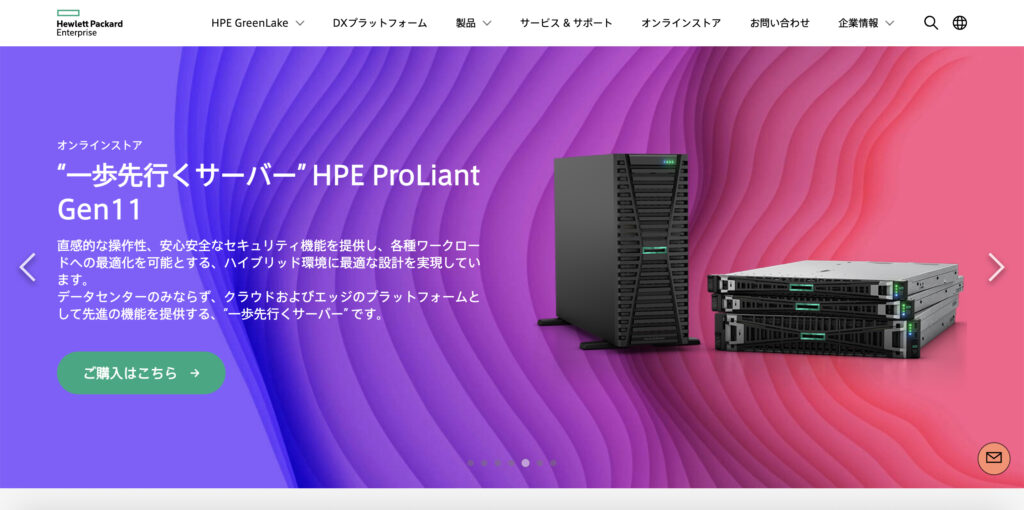
日本ヒューレット・パッカード合同会社
【使用されているタイププロジェクトのフォント】
AXIS Font ベーシック
主にAXIS Font ベーシック Rが全面的に使われています。フォントを統一しウエイト数も絞ったことでミニマルでスッキリとした、とても知的な印象を受けます。
明快かつ知的な表情の文字組みを得意とするAXIS Font ベーシックがとてもマッチしているように思います。また比較的、欧文の入るテキストが多いので、AXIS Fontの特徴の1つでもある和文と欧文を混植した際の相性の良さが効果を発揮しています。
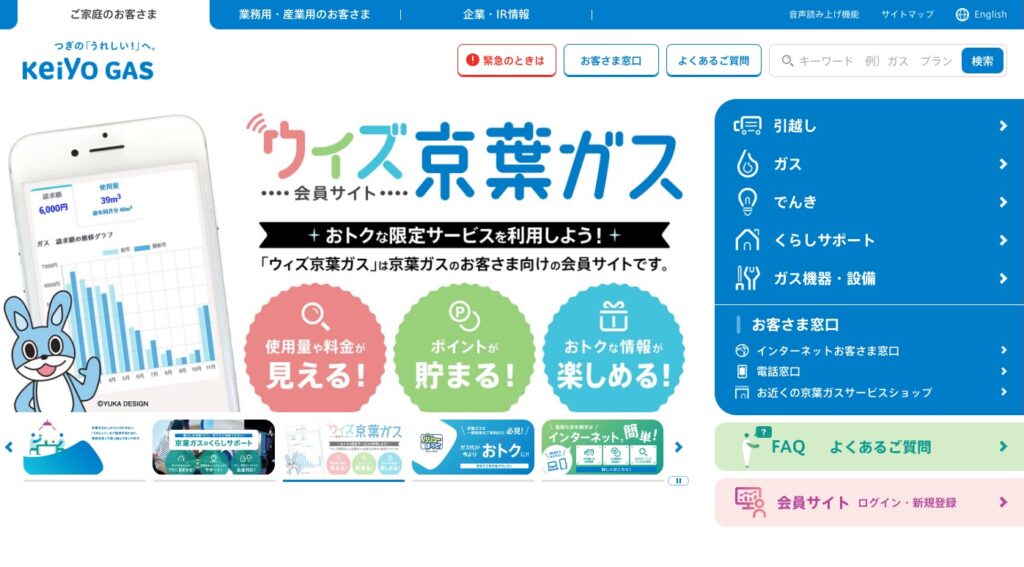
京葉ガス株式会社
【使用されているタイププロジェクトのフォント】
AXIS Font ベーシック
主にAXIS Font ベーシックが全面的に使われています。
伝えなければならない情報が多い場合、煩雑な印象になりがちですが、7つのウエイトが揃っているAXIS Font ベーシックのウエイトを使い分けメリハリをつけることで、このWebサイトの統一感と分かりやすさに貢献できているのではと思います。
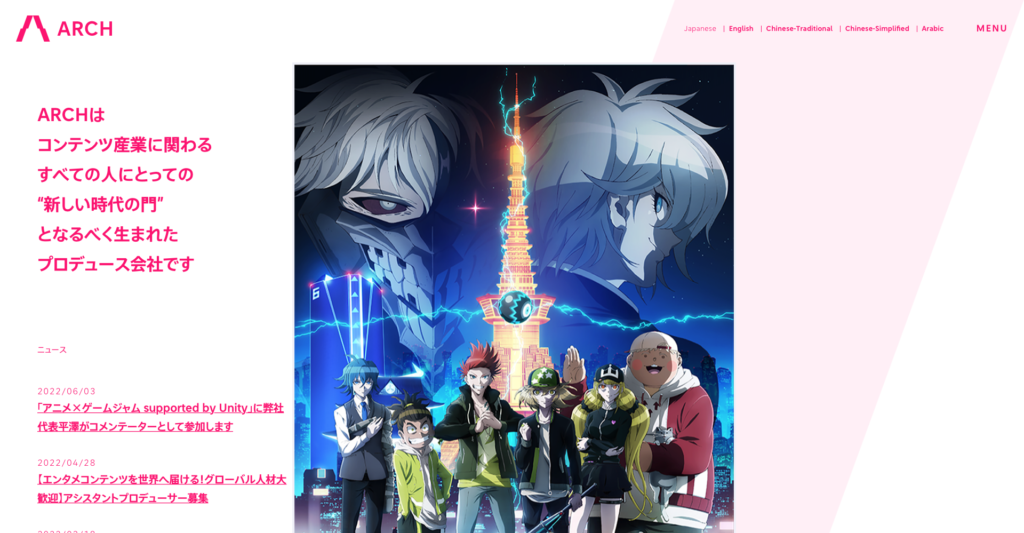
アーチ株式会社
【使用されているタイププロジェクトのフォント】
TPスカイ ローコントラスト
スクリーンで効果を発揮するよう設計されたフォントファミリーの1つであるTPスカイ ローコントラストが全面的に使われています。
鮮やかなピンクとクリアなデザインのTPスカイの組み合わせが新鮮で明るい印象を与えてくれます。また、読字の安定性が高いTPスカイ ローコントラストが小さなサイズのテキストにもスクリーンでの高い可読性を維持しています。